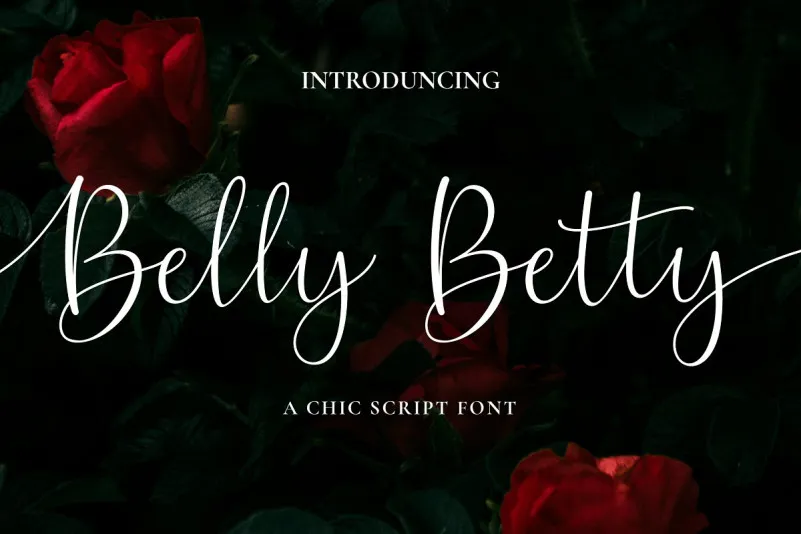
Belly Betty Script Font – Download Grátis
A fonte ‘Belly Betty Script Font’ é apresentada pela Ef_Studio como uma nova tipografia chamada calligraphy script. Ela combina elementos modernos com um toque de elegância, oferecendo diferentes estilos alternativos e adoráveis “swashes”, que dão à letra um ar natural e sofisticado. Ideal para qualquer projeto especial, essa fonte é perfeitamente adaptável tanto para trabalhos de design gráfico quanto escrita por designers experimentando novos estilos de autoria. Com uma base de traços variados e linhas suaves, ela também mantém uma profundidade única, tornando-a um recurso valioso para quem busca uma mistura atraente entre elegância e modernidade na sua tipografia.